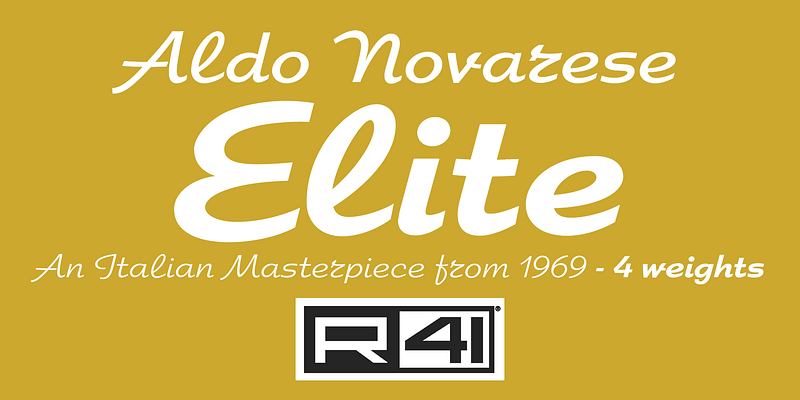
La colección de fuentes más completa y representativa creada por el diseñador tipográfico italiano Aldo Novarese para Nebiolo Foundry y R41.
La colección Aldo Novarese
Las fuentes más emblemáticas de la legendaria casa tipográfica Nebiolo de Turín, diseñadas por Aldo Novarese, digitalizadas a partir de su diseño original y completamente auténticas.